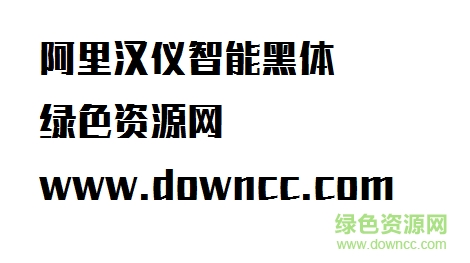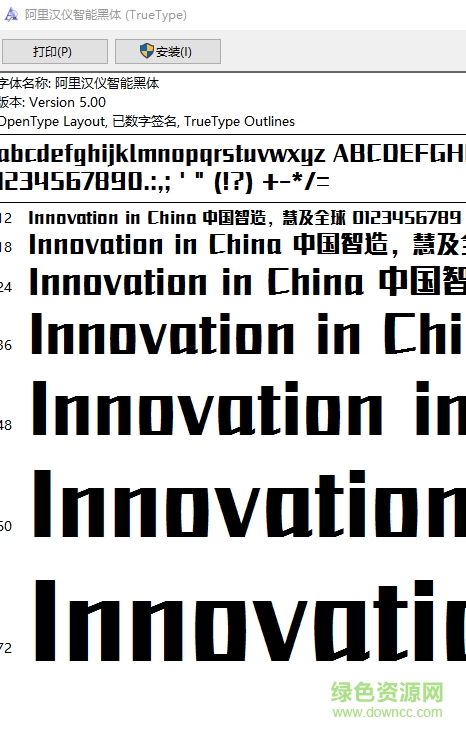
阿里漢儀智能黑體是首款應用于電商行業(yè)的黑體軟件,該字體粗黑精細程度適中,辨識度很高,整體效果大方好看,還有更多類似字體歡迎來綠色資源網下載體驗!
阿里漢儀智能黑體基于黑體的橫豎基本特征,加大橫豎粗細比例,字面飽滿填充整個內框,讓字體更加醒目,視覺沖擊力極強,能夠很好的與用戶對話,非常適用于電商類廣告設計。電商字體通用性極強,適用于絕大多數品類的商品。智能黑體區(qū)別于常規(guī)黑體,剛中帶柔,筆畫的走勢上融入了手寫的方式,整體方正但又不失趣味,度量把握適中。
阿里漢儀智能黑體,字形由漢儀字庫的字體設計師黃珍元主創(chuàng)設計,字庫產品協(xié)同阿里人機自然交互實驗室,通過強大的計算能力自學生成。這款字體是基于阿里巴巴電商平臺應用場景下產生的新分類字體 —— 電商字體。